อ่านยาก = ลูกค้าหนี! เทคนิคเลือก ‘ฟอนต์ (Font)’ งานพิมพ์ ให้สวยคมชัด สื่อสารตรงจุด
การออกแบบสื่อสิ่งพิมพ์ที่สวยงามอาจไร้ความหมายหากผู้รับสารไม่สามารถอ่านข้อความได้อย่างสะดวกสบาย การเลือกฟอนต์ที่ไม่เหมาะสมเป็นหนึ่งในปัจจัยสำคัญที่ทำให้ลูกค้าเมินเฉยต่อสารที่ต้องการจะสื่อ บทความนี้จะนำเสนอเทคนิคการเลือกฟอนต์ (Font) สำหรับงานพิมพ์ เพื่อให้ได้ผลงานที่สวยงาม คมชัด และสื่อสารได้อย่างตรงจุด
หัวใจสำคัญของการออกแบบสิ่งพิมพ์ที่ทรงประสิทธิภาพ
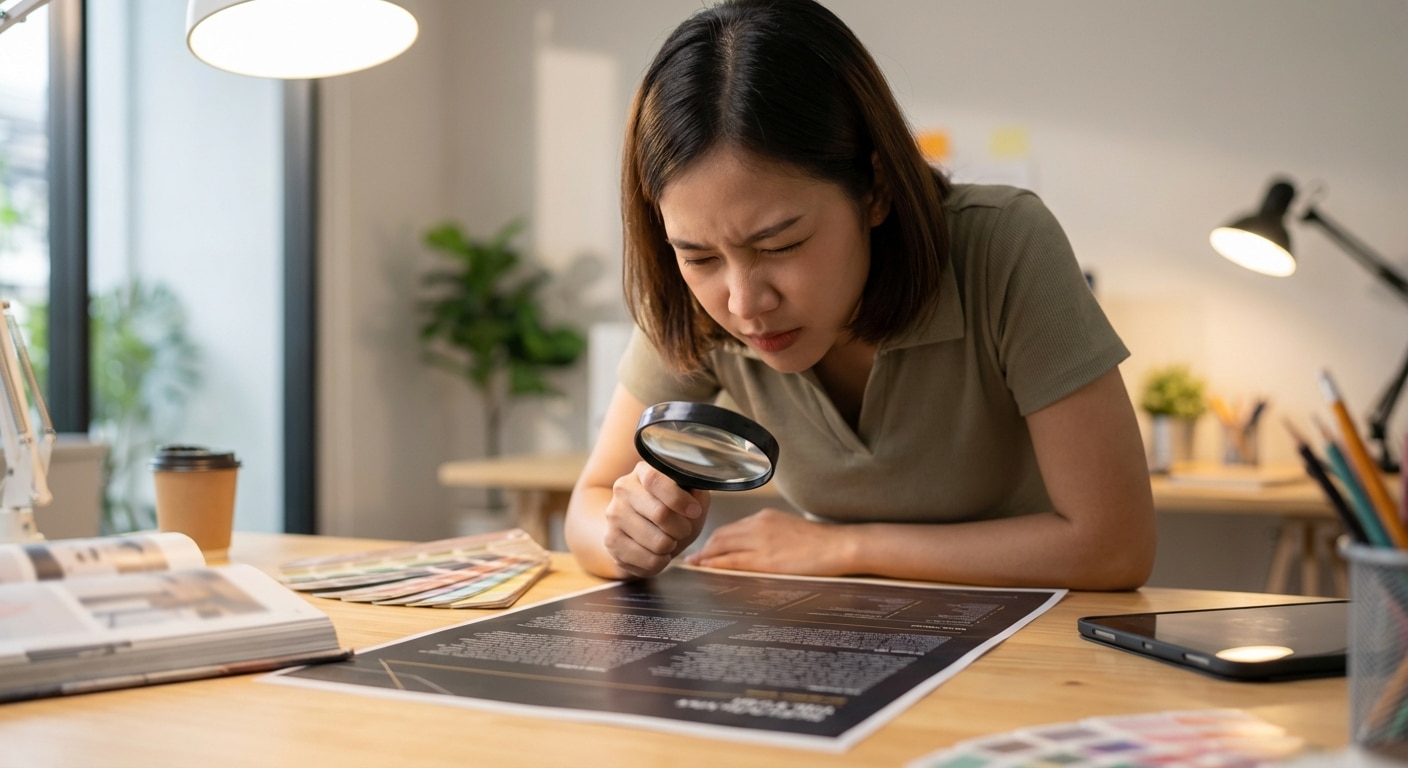
- ให้ความสำคัญกับความชัดเจน: ฟอนต์ที่อ่านง่ายคือพื้นฐานของการสื่อสารที่มีประสิทธิภาพ หลีกเลี่ยงฟอนต์ที่ตกแต่งมากเกินไปจนบดบังเนื้อหา
- ขนาดและน้ำหนักต้องเหมาะสม: ขนาดตัวอักษรสำหรับเนื้อหาหลักไม่ควรเล็กกว่า 7pt และควรเลือกน้ำหนักเส้น (Weight) ให้ตัดกับสีพื้นหลังอย่างชัดเจน เพื่อป้องกันปัญหาหมึกพิมพ์กลืนตัวอักษร
- เข้าใจความแตกต่างของฟอนต์: ฟอนต์มีหัว (Serif) เหมาะสำหรับเนื้อหาขนาดยาวที่ต้องการความน่าเชื่อถือ ส่วนฟอนต์ไม่มีหัว (Sans Serif) ให้ความรู้สึกทันสมัย เหมาะกับพาดหัวหรืองานออกแบบที่ต้องการความเรียบง่าย
- การจับคู่ฟอนต์อย่างมีกลยุทธ์: การใช้ฟอนต์ที่แตกต่างกันสำหรับหัวข้อและเนื้อหาช่วยสร้างลำดับชั้นทางสายตาและทำให้งานออกแบบน่าสนใจยิ่งขึ้น
ทำไมการเลือกฟอนต์จึงเป็นเรื่องสำคัญ?
ในโลกของการออกแบบสิ่งพิมพ์ การเลือกใช้ฟอนต์ที่เหมาะสมถือเป็นองค์ประกอบหลักที่ไม่สามารถมองข้ามได้ เพราะเป็นเครื่องมือสำคัญในการสื่อสารข้อความไปยังกลุ่มเป้าหมาย หากเลือกฟอนต์ผิดพลาด อาจส่งผลให้งานออกแบบที่ตั้งใจสร้างสรรค์มาอย่างดีกลับล้มเหลวในการสื่อสาร ทำให้ผู้รับสารรู้สึกว่า อ่านยาก = ลูกค้าหนี! เทคนิคเลือก ‘ฟอนต์ (Font)’ งานพิมพ์ ให้สวยคมชัด สื่อสารตรงจุด จึงเป็นสิ่งที่นักออกแบบและเจ้าของธุรกิจต้องให้ความสำคัญเป็นอันดับแรก
ฟอนต์ไม่ได้เป็นเพียงแค่ตัวอักษรที่เรียงต่อกัน แต่ยังเป็นองค์ประกอบที่สร้างบุคลิกภาพและกำหนดอารมณ์ของงานออกแบบทั้งหมด การเลือกฟอนต์ที่สอดคล้องกับอัตลักษณ์ของแบรนด์และเหมาะสมกับประเภทของสื่อสิ่งพิมพ์ เช่น นามบัตร โบรชัวร์ หรือเมนูอาหาร จะช่วยเสริมสร้างภาพลักษณ์ที่เป็นมืออาชีพและน่าจดจำ ในทางกลับกัน ฟอนต์ที่อ่านยากหรือดูไม่เข้ากับบริบท สามารถทำลายความน่าเชื่อถือและทำให้ผู้รับสารรู้สึกไม่อยากอ่านต่อได้ในทันที
เจาะลึกประเภทฟอนต์ไทยและหลักการจับคู่
ฟอนต์ภาษาไทยมีโครงสร้างที่เป็นเอกลักษณ์และสามารถแบ่งออกเป็นประเภทหลักๆ ได้ตามลักษณะของหัวตัวอักษร ซึ่งการทำความเข้าใจความแตกต่างเหล่านี้เป็นก้าวแรกสู่การเลือกใช้ฟอนต์ได้อย่างมีประสิทธิภาพ
ฟอนต์มีหัว (Serif) ปะทะ ฟอนต์ไม่มีหัว (Sans Serif)
ฟอนต์ไทยสามารถแบ่งตามโครงสร้างได้เป็น 2 ประเภทหลัก ซึ่งแต่ละประเภทก็มีลักษณะและการใช้งานที่แตกต่างกันออกไป:
- ฟอนต์มีหัว (Looped/Serif): หรือที่เรียกกันว่า “ฟอนต์มีเชิง” มีลักษณะเด่นคือมีขีดเล็กๆ ตกแต่งอยู่ที่ปลายของตัวอักษร ฟอนต์ประเภทนี้มักถูกใช้ในเอกสารที่เป็นทางการ เนื่องจากให้ความรู้สึกน่าเชื่อถือ สง่างาม และคลาสสิก ที่สำคัญคือช่วยนำสายตา ทำให้อ่านเนื้อหาที่มีความยาวต่อเนื่องได้ง่าย ไม่เกิดความสับสนระหว่างตัวอักษรที่คล้ายกัน
- ฟอนต์ไม่มีหัว (Loopless/Sans Serif): มีลักษณะเรียบง่าย สะอาดตา ไม่มีขีดตกแต่งที่ปลายตัวอักษร ทำให้ดูทันสมัยและมินิมัล ฟอนต์ประเภทนี้เป็นที่นิยมอย่างมากในสื่อดิจิทัลและงานพิมพ์สมัยใหม่ เนื่องจากอ่านง่ายทั้งบนหน้าจอและบนวัสดุพิมพ์ เหมาะสำหรับพาดหัวข้อความสั้นๆ หรืองานออกแบบที่ต้องการสื่อสารอย่างรวดเร็วและชัดเจน
| คุณสมบัติ | ฟอนต์มีหัว (Serif) | ฟอนต์ไม่มีหัว (Sans Serif) |
| ลักษณะเด่น | มีขีดตกแต่งที่ปลายตัวอักษร (เชิง) | ตัวอักษรเรียบง่าย ไม่มีขีดตกแต่ง |
| ความรู้สึกที่สื่อ | เป็นทางการ, น่าเชื่อถือ, สง่างาม, คลาสสิก | ทันสมัย, มินิมัล, เรียบง่าย, สะอาดตา |
| การใช้งานที่เหมาะสม | เนื้อหาขนาดยาว, เอกสารทางการ, หนังสือ, นิตยสาร | พาดหัว, โลโก้, สื่อดิจิทัล, งานออกแบบที่เน้นความร่วมสมัย |
| ความสามารถในการอ่าน | อ่านง่ายในเนื้อหาต่อเนื่อง (สิ่งพิมพ์) | อ่านง่ายบนหน้าจอและข้อความสั้นๆ |
กลยุทธ์การจับคู่ฟอนต์อย่างมืออาชีพ
เพื่อสร้างสรรค์งานออกแบบที่น่าสนใจและดูเป็นมืออาชีพ การจับคู่ฟอนต์เป็นเทคนิคที่สำคัญ การเลือกใช้ฟอนต์เพียงชนิดเดียวอาจทำให้งานดูราบเรียบเกินไป แต่การใช้ฟอนต์มากเกินไปก็จะทำให้ดูสับสนและไม่เป็นระเบียบ หลักการจับคู่ฟอนต์ที่นิยมใช้มีดังนี้:
- จับคู่ฟอนต์มีหัวสำหรับพาดหัว กับฟอนต์ไม่มีหัวสำหรับเนื้อหา
- จับคู่ฟอนต์ไม่มีหัวสำหรับพาดหัว กับฟอนต์มีหัวสำหรับเนื้อหา
- ใช้ฟอนต์ตระกูลเดียวกันแต่ต่างน้ำหนัก เช่น ใช้ตัวหนา (Bold) สำหรับหัวข้อ และใช้ตัวปกติ (Regular) สำหรับเนื้อหา วิธีนี้ช่วยสร้างความกลมกลืนและเป็นระเบียบ
- เลือกใช้ฟอนต์ที่มีลักษณะสมดุลและไม่ตกแต่งมากเกินไป เช่น Lato, Open Sans หรือ Prompt ซึ่งสามารถใช้ได้ทั้งหัวข้อและเนื้อหาโดยไม่ขัดแย้งกัน
สิ่งสำคัญคือการทดลองวางฟอนต์ที่เลือกไว้คู่กันเพื่อดูว่าเข้ากันได้ดีหรือไม่ก่อนนำไปใช้ในงานออกแบบจริง
หลักการเลือกฟอนต์งานพิมพ์ให้สื่อสารตรงจุด
การเลือกฟอนต์ไม่ใช่แค่เรื่องของความสวยงาม แต่เป็นเรื่องของการสื่อสารที่ต้องอาศัยความเข้าใจในหลายมิติ เพื่อให้แน่ใจว่าสารที่ส่งออกไปนั้นตรงตามวัตถุประสงค์และสร้างผลกระทบที่ต้องการ
ความสามารถในการอ่าน (Readability) ต้องมาก่อน
นี่คือหลักการที่สำคัญที่สุดและไม่สามารถต่อรองได้ ฟอนต์ที่เลือกใช้ต้องอ่านง่ายและชัดเจนตั้งแต่แรกเห็น ควรมีระยะห่างระหว่างตัวอักษร (Letter Spacing) ที่เหมาะสม ไม่ชิดหรือห่างกันจนเกินไป การเลือกฟอนต์ที่สวยงามแต่ซับซ้อนและอ่านยากจะทำลายจุดประสงค์ของการสื่อสารทั้งหมด ไม่ว่าจะเป็นการออกแบบนามบัตรที่ต้องให้ข้อมูลติดต่ออย่างรวดเร็ว หรือโบรชัวร์ที่ต้องอธิบายรายละเอียดสินค้าอย่างชัดเจน
จิตวิทยาของฟอนต์: อิทธิพลต่อการรับรู้
ฟอนต์แต่ละแบบสามารถกระตุ้นอารมณ์และความรู้สึกที่แตกต่างกันในใจของผู้รับสารได้โดยตรง ตัวอย่างเช่น:
- ฟอนต์ลายมือ (Script): ให้ความรู้สึกสนุกสนาน เป็นกันเอง และมีความคิดสร้างสรรค์
- ฟอนต์มีหัว (Serif): สื่อถึงความน่าเชื่อถือ ความเป็นทางการ และความภูมิฐาน
- ฟอนต์ไม่มีหัว (Sans Serif): แสดงถึงความทันสมัย ความเรียบง่าย และความเป็นกลาง
การเลือกฟอนต์ที่ไม่สอดคล้องกับอารมณ์ของข้อความสามารถเปลี่ยนการรับรู้ของผู้รับสารไปได้อย่างสิ้นเชิง ดังนั้นจึงจำเป็นต้องพิจารณาว่าต้องการให้ผู้รับสารรู้สึกอย่างไรเมื่อเห็นงานออกแบบชิ้นนั้น
สอดคล้องกับอัตลักษณ์ของแบรนด์
ก่อนจะเลือกฟอนต์ใดๆ ต้องทำความเข้าใจลักษณะของภาษาไทย วัฒนธรรม และที่สำคัญที่สุดคืออัตลักษณ์ของแบรนด์ (Brand Identity) ฟอนต์ที่ใช้ควรสะท้อนตัวตนของแบรนด์และสอดคล้องกันในทุกๆ สื่อ ไม่ว่าจะเป็นสื่อออนไลน์ สื่อโฆษณา หรือสื่อสิ่งพิมพ์ การสร้างความสอดคล้องกันนี้จะช่วยให้ลูกค้าจดจำแบรนด์ได้ง่ายขึ้นและสร้างภาพลักษณ์ที่แข็งแกร่ง
Typography คืออะไรและเหตุใดจึงสำคัญ
Typography คือ ศิลปะและเทคนิคในการจัดเรียงตัวอักษรเพื่อให้ภาษาที่เขียนมีความชัดเจน อ่านง่าย และน่าดึงดูดเมื่อนำไปแสดงผล มันไม่ใช่แค่การเลือกฟอนต์ แต่ยังครอบคลุมถึงการกำหนดขนาดตัวอักษร, ความยาวบรรทัด, ระยะห่างระหว่างบรรทัด (Leading), และระยะห่างระหว่างตัวอักษร (Tracking และ Kerning) เพื่อสร้างประสบการณ์การอ่านที่ดีที่สุด
Typography ที่ดีจะช่วยชี้นำสายตาของผู้อ่านไปตามลำดับเนื้อหาที่สำคัญ ทำให้ข้อความที่ซับซ้อนเข้าใจง่ายขึ้น และสร้างความรู้สึกโดยรวมให้กับงานออกแบบ ในทางตรงกันข้าม Typography ที่ไม่ดีจะทำให้ผู้อ่านรู้สึกสับสน เหนื่อยล้า และอาจตัดสินใจเลิกอ่านไปในที่สุด นี่คือเหตุผลที่ Typography เป็นหัวใจสำคัญของการออกแบบกราฟิกและการสื่อสารด้วยภาพ
เคล็ดลับเชิงปฏิบัติสำหรับการออกแบบสิ่งพิมพ์
นอกเหนือจากหลักการพื้นฐานแล้ว ยังมีเคล็ดลับเชิงปฏิบัติที่ช่วยให้การเลือกและใช้งานฟอนต์ในงานพิมพ์มีประสิทธิภาพยิ่งขึ้น
ขนาดตัวอักษรที่เหมาะสม
ขนาดของฟอนต์มีผลโดยตรงต่อความสามารถในการอ่าน การกำหนดขนาดต้องพิจารณาถึงประเภทของสื่อและระยะการอ่าน:
- เนื้อหาหลัก (Body Text): สำหรับสื่อที่ต้องถืออ่านในระยะใกล้ เช่น โบรชัวร์หรือหนังสือ ขนาดตัวอักษรควรอยู่ระหว่าง 9-14 pt เพื่อความสบายตา
- ข้อความย่อยหรือคำอธิบายภาพ: สามารถใช้ขนาดเล็กลงได้ แต่ไม่ควรต่ำกว่า 7 pt เพราะจะทำให้เล็กเกินไปจนต้องเพ่งอ่าน
- พาดหัว (Headline): ควรมีขนาดใหญ่กว่าเนื้อหาหลักอย่างชัดเจน เพื่อดึงดูดความสนใจและสร้างลำดับชั้นของข้อมูล
น้ำหนักเส้นและความเปรียบต่าง (Contrast)
ความเปรียบต่างระหว่างสีของตัวอักษรและสีพื้นหลังเป็นสิ่งสำคัญอย่างยิ่ง โดยเฉพาะในงานพิมพ์ที่คุณภาพของหมึกและกระดาษมีผลต่อผลลัพธ์สุดท้าย
ข้อควรระวัง: อย่าใช้ฟอนต์ที่มีน้ำหนักเส้นบาง (Thin หรือ Light) บนพื้นหลังสีเข้ม โดยเฉพาะในงานพิมพ์ขนาดเล็ก เพราะหมึกพิมพ์อาจมีโอกาสซึมหรือขยายตัวเล็กน้อย ซึ่งจะทำให้เส้นที่บางอยู่แล้วถูกกลืนหายไปกับพื้นหลังจนอ่านไม่ออก ควรเลือกใช้ฟอนต์ที่มีน้ำหนักปกติ (Regular) หรือหนา (Bold) เพื่อให้เกิดความเปรียบต่างที่ชัดเจน
การเลือกใช้ฟอนต์ที่มีน้ำหนักเส้นหลากหลายในตระกูลเดียวกันเป็นข้อได้เปรียบ เพราะช่วยให้นักออกแบบสามารถสร้างความเปรียบต่างและความน่าสนใจภายในงานออกแบบชิ้นเดียวกันได้อย่างกลมกลืน
ฟอนต์ไทยสมัยใหม่ที่ได้รับความนิยมในงานพิมพ์
ปัจจุบันมีฟอนต์ไทยสมัยใหม่จำนวนมากที่ถูกออกแบบมาอย่างดีและมีความสมดุลระหว่างความสวยงามกับการใช้งาน ซึ่งเป็นที่นิยมในวงการออกแบบและโฆษณา:
- Sukhumvit Set: เป็นฟอนต์ไม่มีหัวที่ทันสมัย มีโครงสร้างสะอาดตาและอ่านง่ายมาก ทำให้เป็นที่นิยมใช้อย่างแพร่หลายในงานโฆษณาและงานออกแบบร่วมสมัย
- Kanit: ฟอนต์ที่เรียบง่ายแต่มีความหลากหลายสูง สามารถนำไปปรับใช้ได้กับงานเกือบทุกประเภท ให้ความรู้สึกมินิมัลและร่วมสมัย
- Mitr: ฟอนต์ที่มีลักษณะตัวหนาแต่ยังคงความมินิมัลไว้ได้อย่างดีเยี่ยม สามารถคงไว้ซึ่งความรู้สึกทันสมัยและเป็นที่จดจำ
ฟอนต์เหล่านี้เป็นตัวอย่างที่ดีของการผสมผสานระหว่างองค์ประกอบแบบคลาสสิกและร่วมสมัยเข้าด้วยกัน มีรายละเอียดของหัวตัวอักษรที่เหมาะสม ช่วยเพิ่มความเป็นทางการและความซับซ้อนให้กับงานพิมพ์ได้อย่างลงตัว
สรุปแนวทางการเลือกฟอนต์เพื่อความสำเร็จ
การเลือกฟอนต์สำหรับงานพิมพ์เป็นกระบวนการที่ต้องผสมผสานทั้งศาสตร์และศิลป์เข้าด้วยกัน หลักการที่สำคัญที่สุดคือต้องให้ความสำคัญกับความสามารถในการอ่าน (Readability) เป็นอันดับแรก ตามด้วยการเลือกฟอนต์ที่สามารถสื่อสารอารมณ์และสะท้อนอัตลักษณ์ของแบรนด์ได้อย่างถูกต้อง การทำความเข้าใจความแตกต่างระหว่างฟอนต์ประเภทต่างๆ เช่น ฟอนต์มีหัวและไม่มีหัว การกำหนดขนาดและน้ำหนักที่เหมาะสม รวมถึงการจับคู่ฟอนต์อย่างมีกลยุทธ์ จะช่วยยกระดับงานออกแบบสิ่งพิมพ์ให้ดูเป็นมืออาชีพและสื่อสารกับกลุ่มเป้าหมายได้อย่างมีประสิทธิภาพสูงสุด การเลือกฟอนต์ที่ผิดพลาดสามารถบ่อนทำลายแนวคิดการออกแบบที่ดีที่สุดได้ ดังนั้นการใส่ใจในรายละเอียดเล็กๆ น้อยๆ เหล่านี้จึงเป็นกุญแจสำคัญสู่ความสำเร็จ